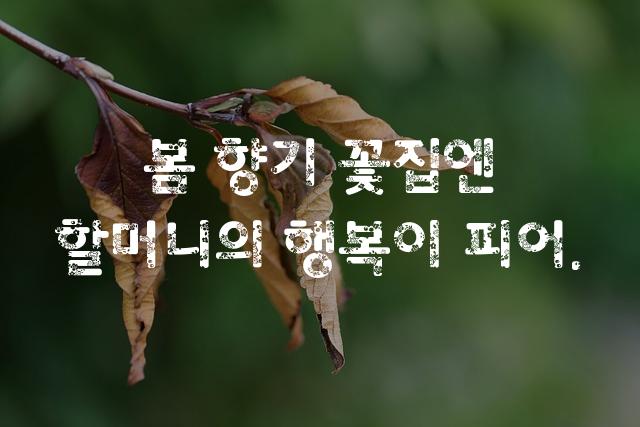
Rix열정도체는 각진 형태와 두꺼운 라인이 특징인 고딕 스타일의 폰트입니다. 꽉 찬 디자인과 장식적 요소가 조화를 이루어 강렬하고 열정적인 분위기를 전달합니다.
Rix열정도체은(는)
기본 고딕, 두꺼운 스타일, 굵은 고딕, 장식 스타일, 네모꼴, 단단함, 별모양/패턴 계열의 생김새를 가지고 있으며
광고 캠페인, 디지털 광고 등에서 자주 활용되며, 효과적인 메시지 전달에 적합합니다.
이 폰트는 광고/마케팅, 엔터테인먼트 분야에 잘 어울리며,
창의적인, 강렬한 느낌을 담고 있는 것이 특징입니다.